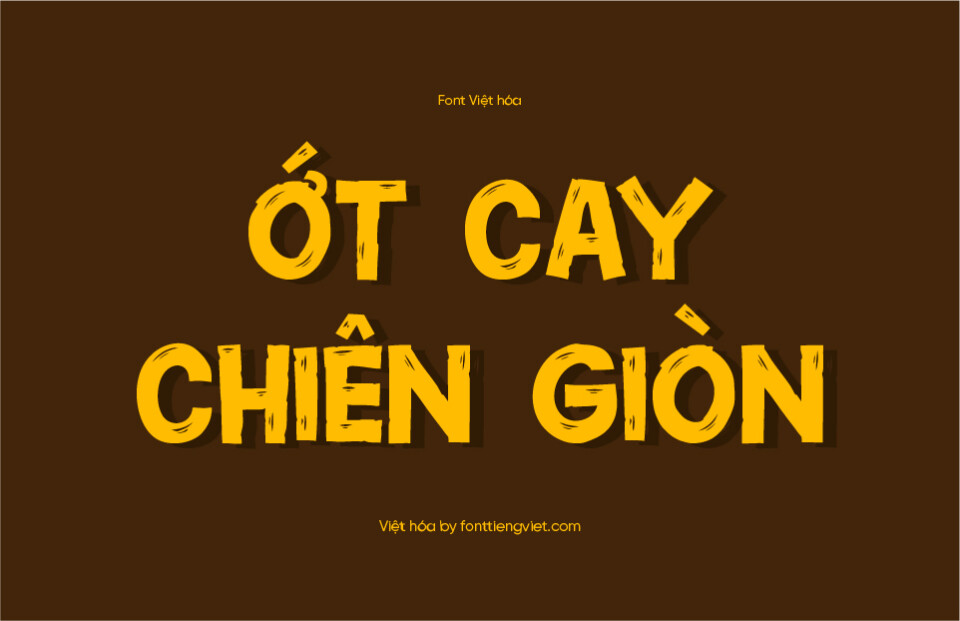
Font Việt hóa 1FTV VIP Potato Chips
Trong thế giới đồ họa hiện đại, việc tìm kiếm một bộ Font Chữ phù hợp chính là chìa khóa để tạo nên sự khác biệt cho tác phẩm của bạn. Nếu bạn đang tìm kiếm một phong cách vui nhộn, năng động và đầy sáng tạo, thì Font Việt hóa 1FTV VIP Potato Chips chính là lựa chọn hoàn hảo nhất. Đây là bộ phông chữ được thiết kế tỉ mỉ, mang lại cảm giác thân thiện và gần gũi, cực kỳ phù hợp cho các dự án thiết kế liên quan đến giới trẻ và học đường. Với phiên bản đã được Font Miễn Phí cung cấp, người dùng có thể dễ dàng sử dụng tiếng Việt mà không lo lỗi hiển thị, giúp quy trình làm việc trở nên trơn tru và chuyên nghiệp hơn bao giờ hết.
Đặc điểm nổi bật của Font Việt hóa 1FTV VIP Potato Chips
Thiết kế sáng tạo và linh hoạt
Font Việt hóa 1FTV VIP Potato Chips gây ấn tượng mạnh nhờ những đường nét bo tròn mềm mại, gợi liên tưởng đến những miếng khoai tây chiên giòn rụm và thú vị. Kiểu dáng của font mang đậm chất trẻ trung, giúp các bài thuyết trình, poster sự kiện hay bìa sách giáo khoa trở nên sinh động hơn. Đặc biệt, bộ font này hỗ trợ đầy đủ các ký tự dấu tiếng Việt, đảm bảo tính thẩm mỹ đồng nhất cho mọi văn bản. Bạn có thể sử dụng nó cho các tiêu đề lớn cần sự chú ý hoặc các đoạn trích dẫn ngắn đầy cảm hứng.
Ứng dụng đa dạng trong học tập
Không chỉ dành cho dân chuyên nghiệp, bộ font này còn rất được lòng các bạn học sinh và giáo viên. Nhờ tính dễ đọc và vẻ ngoài bắt mắt, nó giúp các nội dung giáo dục trở nên bớt khô khan, kích thích sự sáng tạo và ham học hỏi. Việc áp dụng font chữ này vào các thiết kế Canva hay PowerPoint sẽ giúp sản phẩm của bạn nổi bật giữa đám đông.
Để tận dụng tối đa vẻ đẹp của bộ font này, bạn nên kết hợp với những tông màu rực rỡ và hình ảnh minh họa ngộ nghĩnh. Đừng ngần ngại thử nghiệm Font Việt hóa 1FTV VIP Potato Chips cho các dự án cá nhân hoặc cộng đồng. Hy vọng rằng với chia sẻ từ Font Miễn Phí, Font Việt Hóa, Font Việt hóa 1FTV VIP Potato Chips, bạn sẽ có thêm nguồn cảm hứng mới để hoàn thiện những ý tưởng độc đáo của mình một cách dễ dàng và hiệu quả nhất.